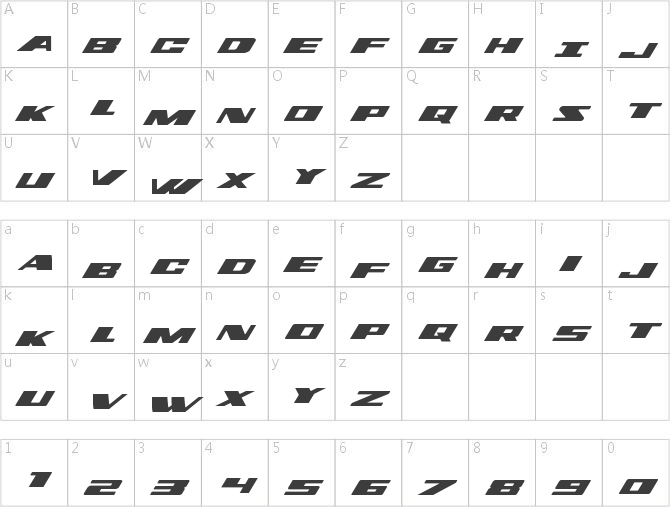
Dassault Expanded Italic
Dassault Expanded Italic介绍
Dassault Expanded Italic字体字库是一款让人赏心悦目、百看不厌的英文字体,适合各类广告和产品包装设计应用,字体大小0.03MB,格式为ttf字体,上传用户是星期一,作者/版权方为未知